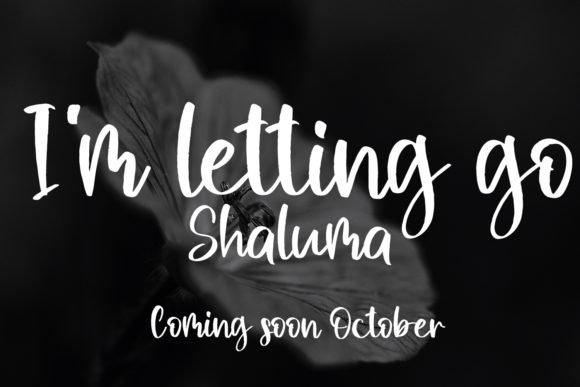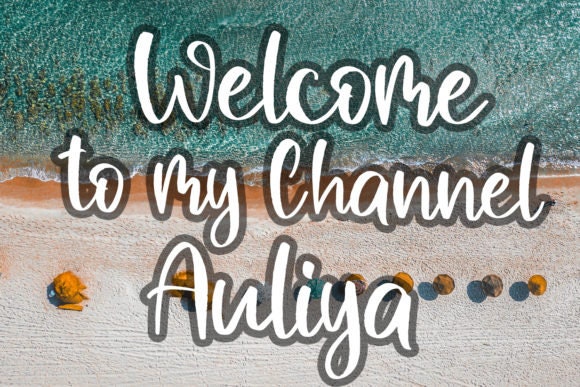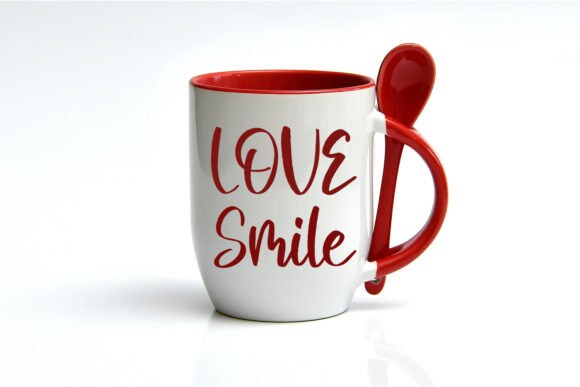
エレガントな手書きの魅力をまとったスクリプトフォント、Diamonds。流麗なカリグラフィーの筆致に、さりげないセリフのニュアンスを加え、クラシックとモダンが調和した洗練をもたらします。ウェディング招待状からブランドロゴまで、読みやすさと上質感を両立したタイムレスな美しさが輝きます。
結婚式やパーティーシーンに最適。招待状、セーブ・ザ・デート、席札、メニュー、サンクスカードを美しく格上げします。滑らかに繋がるストロークが温かみと親密さを演出し、整った字形設計により印刷物でもデジタルでも優れた可読性を実現。ロゴ、パッケージ、SNSビジュアル、ブランドツールなど、信頼感とエレガンスを求める場面でデザイナーやスモールビジネスに愛されています。
Procreateをはじめ各種デザインアプリとの相性も抜群。名言レタリングやグリーティングカード、名刺デザインまで、なめらかなリズムがレイアウトを端正にまとめます。モダンな対比にはシンプルなサンセリフを、ヘリテージ感にはクラシックなセリフ体を組み合わせて。
主な特長とメリット:
- ラグジュアリーな印象を生む、カリグラフィーのエッセンスを備えた上品な手書きスクリプト
- さりげないセリフ要素で個性と高い可読性を両立
- ウェディング文具、ロゴ、ブランディング、引用、グリーティングカード、名刺に最適
- スムーズな運筆と均整の取れたスペーシングで、プロの仕上がりを手軽に
- 印刷からデジタルまで幅広く活躍—パッケージからSNS投稿まで対応
タイポグラフィにひときわの輝きを。Diamondsは、美しさと明瞭さ、そして愛らしい余韻が必要なときに手に取りたくなる定番クオリティのスクリプトです。メッセージを格上げし、見る人を惹きつけ、言葉にダイヤモンドのようなきらめきを与えましょう。